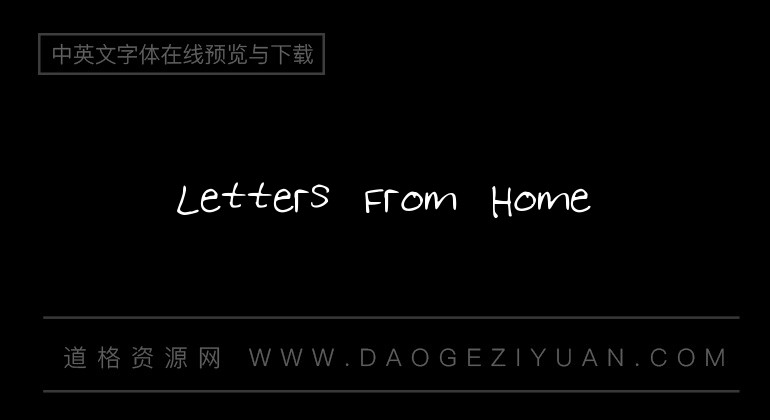
Letters From Home 是一款温暖的手写字体,由设计师Laura Worthington设计。这款字体具有温暖、舒适的感觉,它看起来就像是一封久违的家乡信件,让人回想起曾经的家乡和童年时光,充满温馨的回忆。Letters From Home字体有两种字体样式:斜体和粗体,每种样式都有许多细节,可以用于不同的设计项目。内容介绍
Letters From Home是一款非常不错的手写艺术字体,具有很好的视觉感,适合于文化类的宣传设计、商业类品牌的广告和产品包装设计以及个性化文字排版等较多场景。